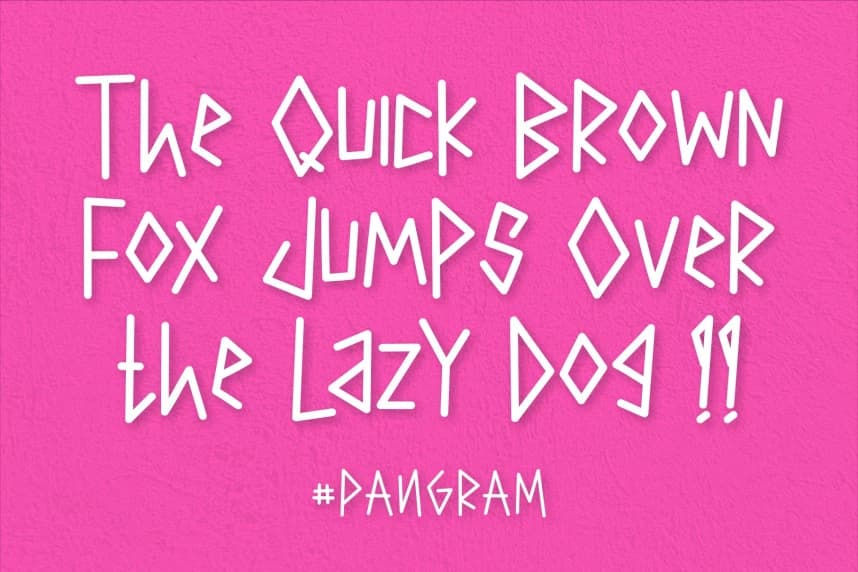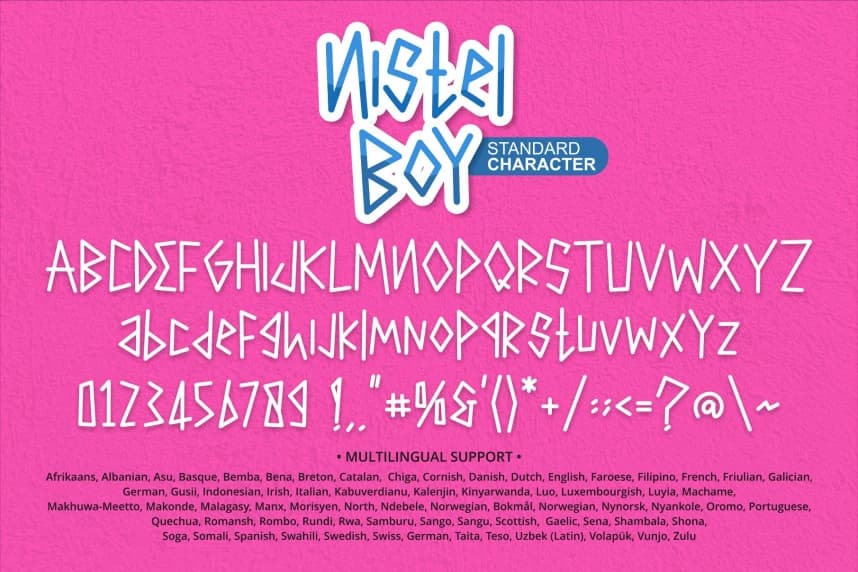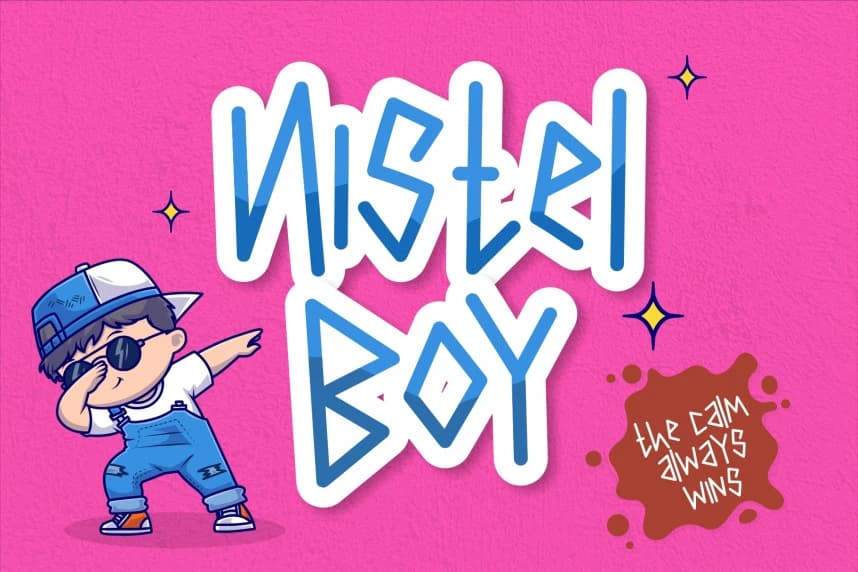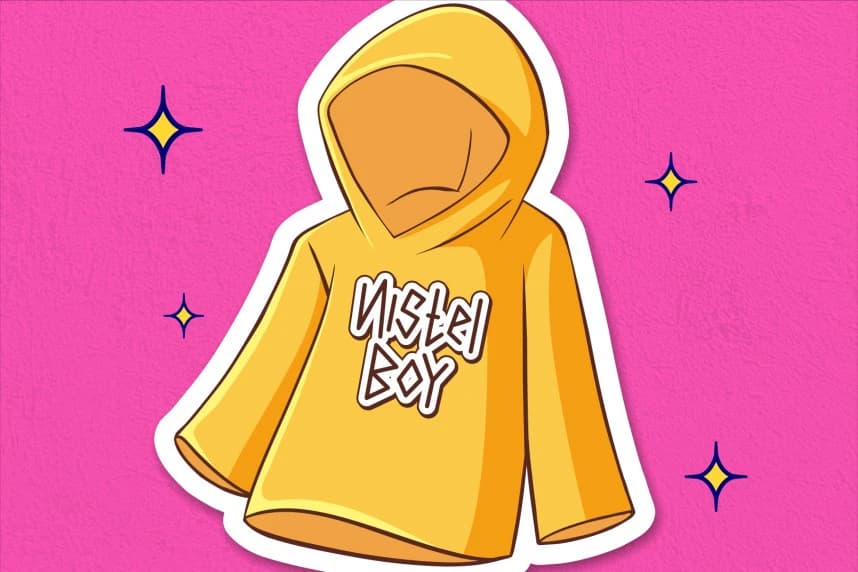
Nistel Boy Font, posterler, logolar, dergiler, kapaklar, afişler ve çok daha fazlası için sevimli bir gösteri yazı tipidir. Bu muhteşem yazı tipini edinin ve onu güzel tasarımlar yaratmak için kullanın. Oldukça geniş bir proje yelpazesine kolayca uyum sağlar, bu yüzden yaratıcı fikirlerinize ekleyin
Nistel Boy Font, posterler, logolar, dergiler, kitap kapakları, afişler ve çok daha fazlası için mükemmel olan sevimli bir gösterim yazı tipidir! Bu harika yazı tipini edinin ve hoş tasarımlar yaratmak için kullanın. Çok geniş bir proje yelpazesine kolayca uyum sağlar; bu yüzden yaratıcı fikirlerinize ekleyin ve tasarımlarınızın öne çıkmasına nasıl yardımcı olduğunu görün!